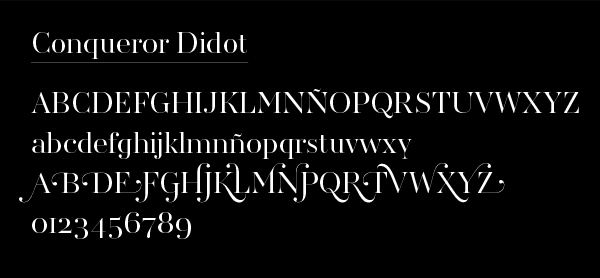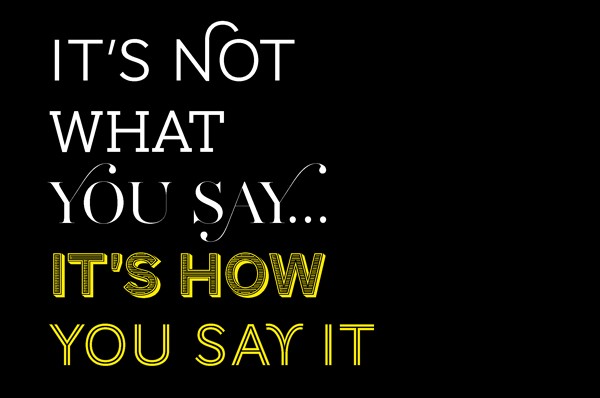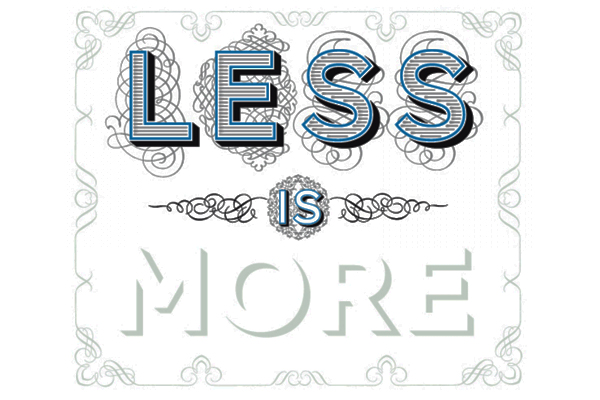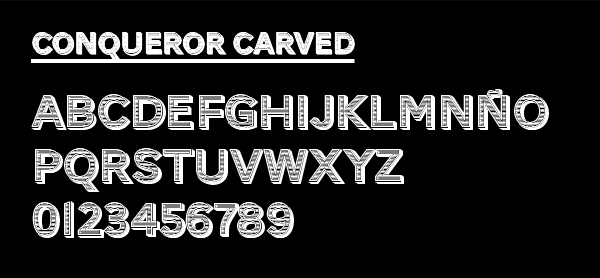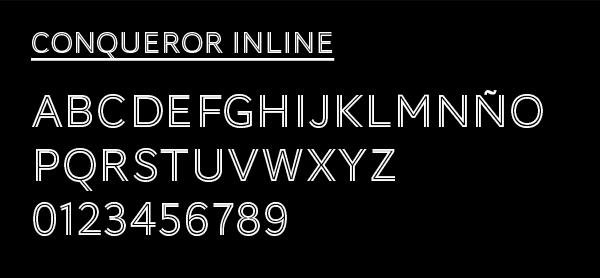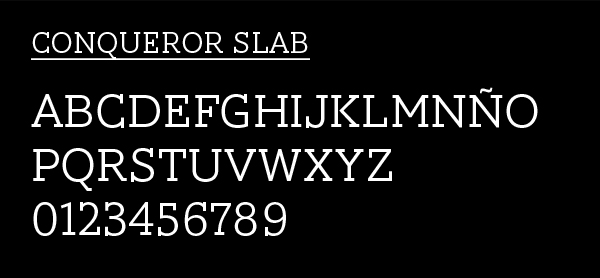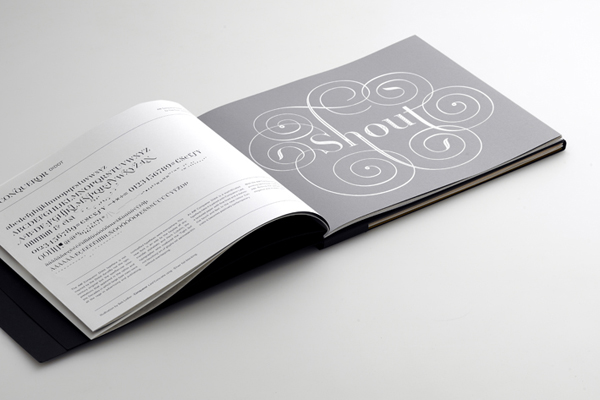
Jean François Porchez diseña cinco tipografías AW Conqueror
El tipógrafo francés diseña en exclusiva para Conqueror cinco tipografías de descarga gratuita, las familias AW Conqueror se presentan en acabados evocadores de diferentes periodos históricos y sus cánones tipográficos. AW Conqueror Sans, AW Conqueror Didot, AW Conqueror Inline, AW Conqueror Slab y AW Conqueror Carved son de amable combinación entre sí pues siguen la misma estructura básica.
Asimismo, en colaboración con la compañía The Beijing Founder Electronics, han desarrollado una tipografía china, también de libre descarga únicamente para empleo personal.
Ilustración de Seb Lester para Conqueror realizada con la AW Conqueror Carved de J. F. Porchez.
Entre los trabajos de Jean François Porchez destaca la creación de la nueva tipografía del diario Le Monde en 1994. Es fundador Typofonderie, desde donde distribuye internacionalmente sus trabajos; y asimismo presidente honorario de la Asociación Internacional de Tipografía (ATypl), fundador de la asociación Le Typographe y ha sido galardonado con el premio Charles Peignot a la excelencia tipográfica en 1998.
Catálogo de la familia Conqueror y la nueva serie de papeles Conqueror.
AW Conqueror Sans se inspira en las fuentes utilizadas en Europa entre la I y II Guerra Mundial. De líneas geométricas evoca el espíritu de la Bauhaus y Art déco.
AW Conqueror Didot, inspirada en las interpretaciones de la dinastía Didot en los años 1960 y 1970. Rrinde homenaje a la época de la trasferencia en seco y a Herb Lubalin, tipógrafo creador de glifos sin superposiciones.
AW Conqueror Slab se inspira en las tipografías de serifa geométrica cuadrada de los años 1930.
AW Conqueror Carved incluye efectos de profundidad y relieve muy utilizadas en el siglo XIX, e invita a jugar con los volúmenes y los colores en la impresión.
AW Conqueror Inline, inspirada en Nobel inline, una fuente del siglo XX creada por S.H. de Ross.